艺术字体可以在人眼中效果更佳,通过该视觉的优化设计能够为商家品牌的推广作出贡献,而且也涌现了诸多个人的艺术字,炫酷多变的艺术字在结构处理和展示方面有了新的定位,它也充分的表达出它的魅力,根据个人性格和喜好等设计艺术字体,设计时需要注意哪几点呢?如何将设计的字体进行推广呢?
为加强艺术字连接,可将前面和后面的字进行笔画的连接,通过这种关系和设计手法让艺术字显得更有设计感,更有活力感。如一些商用艺术字用作KTV,则要表现出休闲娱乐,这种属性是相互关联的,设计艺术字体要把轻松的氛围充分的表现出来,包括颜色、图形、艺术字笔画、内部的一些连接,都有一个目的功效——让别人看到这个字之后,能够联想的这个品牌,能够记住这个品牌(如字体视界),能够享受这个品牌所带来的舒适。
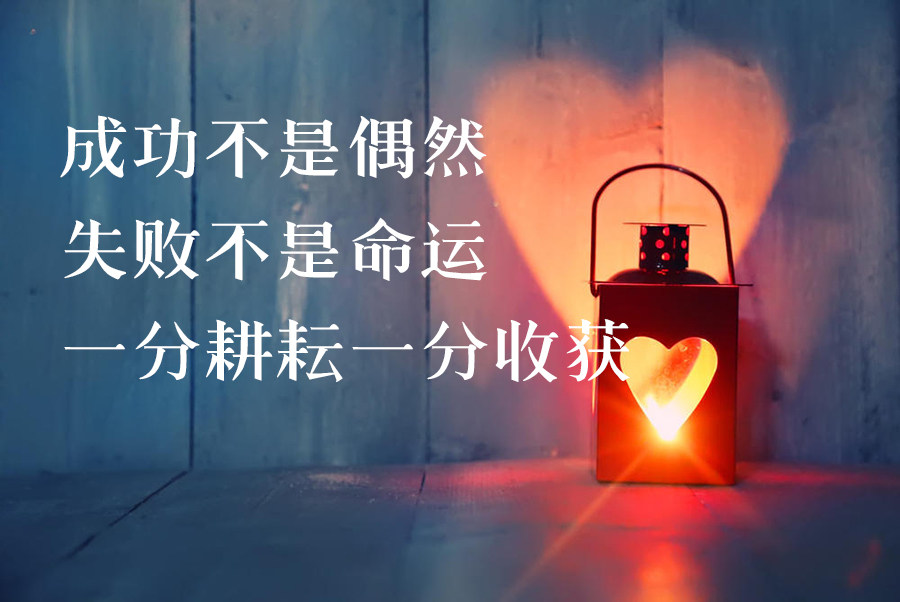
设计艺术字体即比较清新一点、比较优雅一点的风格,可借鉴黑体字的一些设计形式,然后用钢笔造字法设计方法进行完整的设计,看了之后给别人的感觉是比较轻松的格调,这是完全不同的气氛和表达,做这样的艺术字要尽量简约、有气质感。把产品、品牌背景、含义提炼并表现出来,让别人看到这个字之后,能够明白这个品牌的目的,无论是艺术字体设计、艺术字造字,字体视界内字体很多夹杂着关于个人的情感。
需要根据类别进行数据性设计,若为个人设计,则需看艺术字体的效果是否与个人相匹配?设计艺术字体是一种视觉数据艺术,虽然目前已取得了令人瞩目的成绩,但是在识别生成和自动性优化方面仍要做出努力。